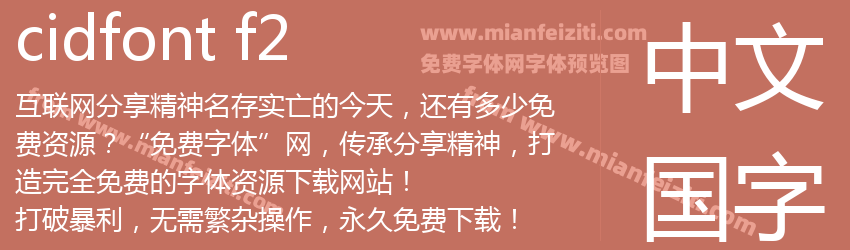
cidfont f1字体也就是微软雅黑字体,字体简单,可辨识度高,字库完整,适合多种场合字体的设计,比如海报设计、包装设计和论文制作等,cidfont f1英文字体已经很难找了,这里提供出来,需要的朋友赶快下载吧!
CID格式是美国Adobe公司发表的最新字库格式,它具有易扩充、速度飞快、兼容性好、简单、灵活等特点,已成为国内开发中文字库的热点,也为广大网友使用字库提供质量更好,数量更多的字体。
现在用的比较多的就是cidfont+f1字体,cidfont+f2字体,cidfont+f3字体,就算这样,用户还是很少很少。
本款“Microsoft Ya Hei Regular”是一款书写很新颖的字体,字体大方,适合各种设计作品使用!欢迎下载!